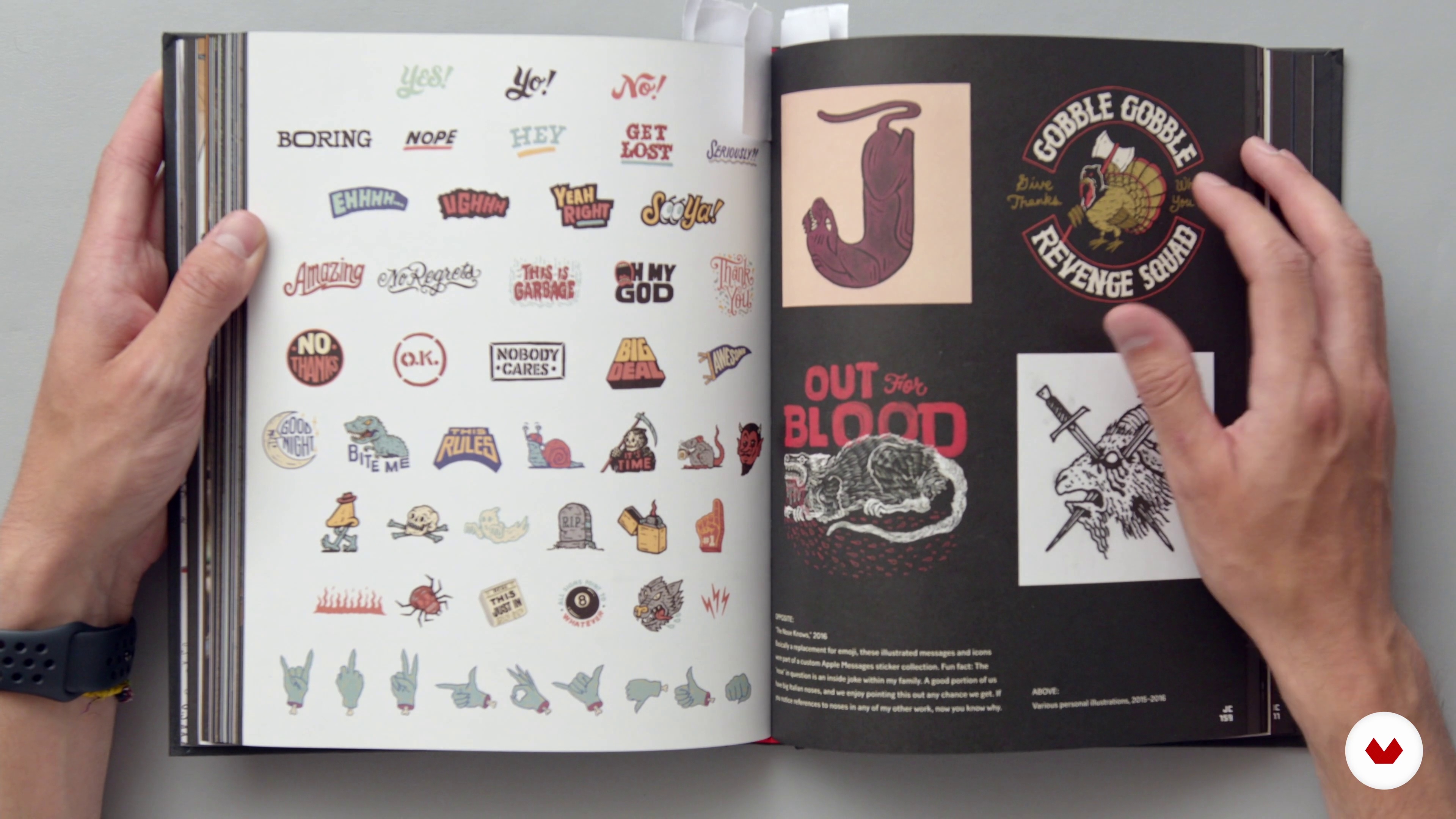
Typographie expressive en mouvement avec After Effects
Influences
À propos de la leçon : Influences
“Nous allons maintenant jeter un coup d'œil à certains de mes premiers points de référence, ainsi qu'à des artistes incroyables qui créent des œuvres de type lumineuses, amusantes, expressives et positives.”
Dans cette leçon, Mat Voyce aborde le sujet : Influences, qui fait partie du cours Domestika en ligne : Typographie expressive en mouvement avec After Effects. Apprenez à créer des lettres aux formes pleines de personnalité et à leur donner vie de façon ludique grâce à l'animation.
“Influences Influences, considérez-les comme votre arsenal de designer. C'est quelque chose auquel tu peux te référer, quelque chose que tu peux garder près de toi lorsque vous concevez et créez quelque chose de nouveau. Dans cette leçon, je vais vous montrer quelques-uns de mes favoris d'enfance, quelques artistes des temps modernes, qui repoussent les limites de la typographie et de l'illustration. Tout d'abord, je vais passer directement à l'un de mes livres préférés. "Brand by Hand" est par un designer appelé Jon Contino. Il est un designer, illustrateur, créatif basé à New York. Ce gars...”